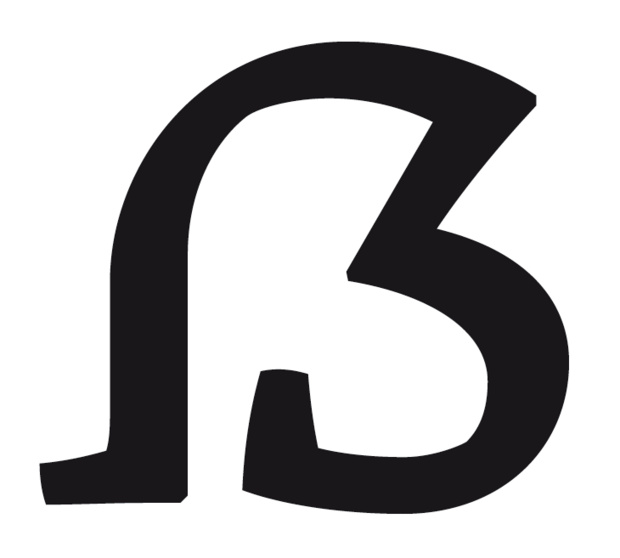
Skolar vs. Marat
nachdem die skolar jetzt nachwuchs in form einer light und eine extrabold
bekommen hat, werde ich wohl kommende woche die entscheidung zwischen
marat und skolar treffen müssen – eine der beiden wird gekauft.
ich sehe allerdings gerade das im typojournal 3 ein versal-ß in die skolar gerutscht ist,
ist das standard oder handgemacht?
gut ausgebaut sind beide, die marat kommt mit einem extra schnitt 'fat'
die skolar hat dafür schönere stylistic sets, sowie griechische und cyrillische glyphen.
ich sehe allerdings gerade das im typojournal 3 ein versal-ß in die skolar gerutscht ist,
ist das standard oder handgemacht?
Das ist dem Bild ist von mir und in Zusammenarbeit mit Veronika Burian für das TJ3 entstanden. Allerdings haben wir in der Diskussion darum den Designer dann auch noch rumgekriegt und er hat dann in das kürzliche Update der Schrift ein ganz ähnliches ẞ eingebaut. Ansicht und die Versionen wo das enthalten ist siehe hier:
Da hast Du Dir ja zwei wahre Leckerbissen ausgesucht!
Die Skolar habe ich sofort ins Herz geschlossen, weil sie nicht so »glatt« daher kommt. Eine sehr lebendige und eigenständige Schrift.
Aber auch die Marat ist sehr reizvoll. Bloß das g der Marat gefällt mir überhaupt nicht.
Wenn die Skolar tatsächlich ein Versal-Eszett haben sollte, wäre das mein Favorit.
Ich hatte mich eben auch noch etwas für Dich umgesehen. Die FF More wäre noch sehr »reichhaltiges Frischfleisch«, aber auch die FF Milo Serif hat ihren Charme (in Kombi mit der der Sans ein toller CD-Font).
Aber die Skolar scheint sie momentan alle zu übertreffen. Meinen Segen hast Du! ; )
@ RoMi: Was die Entscheidung Skolar vs. Marat angeht: Wenn nicht eine von beiden wesentlich besser ausgebaut ist als die andere, dann dürfte die Entscheidung für eine der beiden ja eher nach ästhetischen Gesichtspunkten fallen, oder? Ich selber würde mich für die Skolar entscheiden, mir gefällt ihre etwas robustere Erscheinung und die Kursive hat mich auch gleich überzeugt. Die Marat wirkt eleganter auf mich. Auch schön. Aber für meinen Geschmack (in Relation zur Skolar) etwas zu rund und zu glatt. Außerdem: Die Skolar hat ein ẞ! Um die Erfolgsgeschichte Versal-Eszett voranzutreiben müssen wir sie jetzt alle kaufen. Auch wenn Du gar keine Versalien verwendest. ;-)
Um die Erfolgsgeschichte Versal-Eszett voranzutreiben müssen wir sie jetzt alle kaufen.
:nicken: Ich glaube, wir sollten uns generell nur noch auf Versal-Eszett-Fonts einlassen. Ja, Erfolg hat eben auch immer seinen Preis! :nicken:
hmm. ihr macht es mir nicht leichter ;)
das mit dem versal-ß ist schon mal ein super plus für die skolar.
weisst du wie lange ich gesiebt habe um nur noch zwischen diesen
beiden perlen wählen zu müssen? nein, quark. danke für die tipps.
die ff milo fäll rausaus, weil sie mir zu sehr brushstroke ist (siehe: a)
die ff more ist wirklich hübsch und hatte ich so noch nicht auf dem schirm,
war eher in richtung meta serif bei FF unterwegs, allerdings kostet die pro
um einiges mehr im vergleich zu skolar und marat. theoretisch brauche ich
diese ganzen sprachunterstützungen nicht, allerdings würde ich bei marat
und skolar jeweils die pro kaufen, da ich den preis fair finde.
die italic ist nicht so mein fall, dafür aber insgesamt eine schöne familie.
ich mag eigentlich eher die skolar, weil sie nicht so glatt ist. allerdings hab ich
angst das ich mich daran irgendwann satt gesehen habe. vorallem die italic
ist ja doch eher eigen und ich such eigentlich ein arbeitstier die nicht sooo
aufällig sein soll. die italic der marat ist dafür ziemlich aalglatt ... und dann
ist dann noch das tolle 'a' der marat, in da sich mich sofort verguckt habe, ich
bin ja neben R- und S- ein totaler a-fetischist. :ilovetype:
momentan stets 2:1 für die skolar.
ich bekomme grad die pdfs nicht runtergeladen, deswegen hier die frage: kann skolar polytonisches griechisch oder nur monotonisches?
… ich bin ja neben R- und S- ein totaler a-fetischist. :ilovetype:
Ja das geht mir ähnlich. Was bei Dir das S ist, ist bei mir das g. Da schaue ich immer zuerst hin. Das Mara-a hat mich auch sofort angesprungen. Aber ich bleibe dabei, die Skolar ist mir in Ihrer Gesamtwirkung viel sympathischer. Bei der Mara schwingt für mich irgendwie so etwas »Arrogantes« mit. Hat die eigentlich auch so schöne Pfeile? (Habe nirgends die gesamte Glyphenübersicht gefunden.)
Mit der FF Meta Serif hatte ich auch schon mal sympathisiert. Aber die war mir dann schon wieder zu »gelutscht«. Die Skolar »prickelt« da noch mehr in den Augen. Schade, dass sie kein Sans-Bruder hat. (Ich habe immer gern das Gesamtpaket – hast Du eigentlich schon die Vista-Familie? :-|)
außen vor lässt.
die vesper ist auch sehr hübsch, wenn auch nicht ganz so weich wie die skolar,
kommt insgesamt etwas zackiger daher, was ich aber nicht schlecht finde.
die vesper wäre eine super alternative zur skolar, was allerdings dagegen spricht
ist der preis der pro-version (über 400 euro) und dann auch nur für eine lizenz.
weniger gefällt mir die offene form von R und B, dass R nutze ich ja doch recht oft
und da würde ich mich jedesmal daran stoßen.
neee ... ich bleib bei der skolar ;)